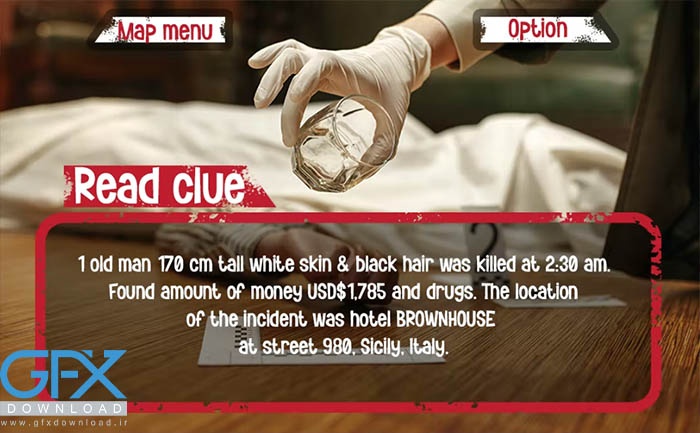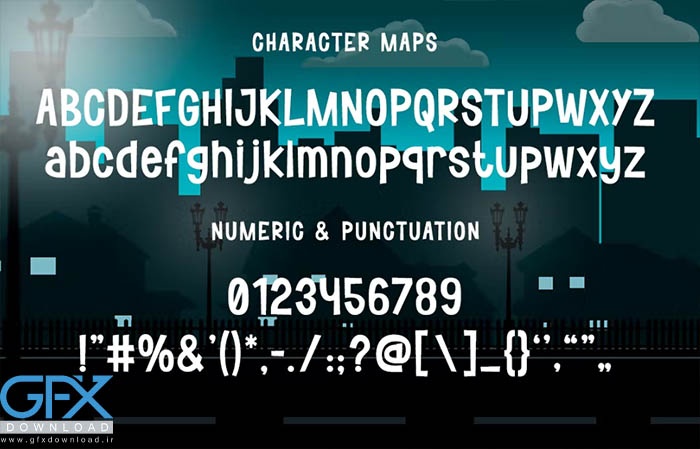
این فونت رایگان مناسب برای بازی ها کارآگاهان/کتاب های معمایی، بازی های آنلاین، پوسترهای رویداد، فونت وسایل مدرسه، پوسترها، عناوین فیلم ها، جلدهای یوتیوب، تصاویر کوچک یوتیوب، جلد صفحات رسانه های اجتماعی و غیره... می باشد. دانلود رایگان فونت بازی Flicker از جی اف ایکس دانلود با لینک مستقیم در ادامه مطلب.
فونت بازی Flicker
فونت انگلیسی رایگان بازی Flicker
• پایه لاتین A-Z و a-z، اعداد، علائم نقطه گذاری